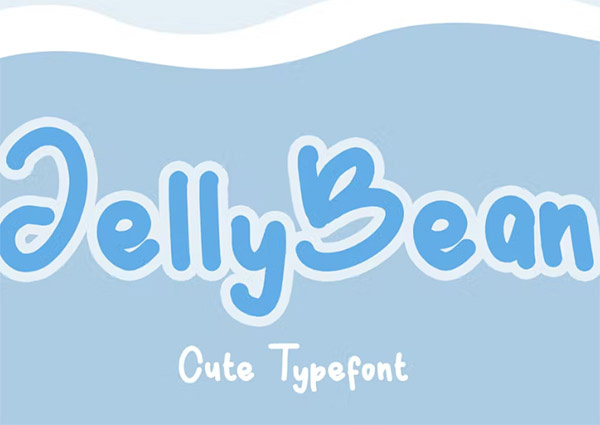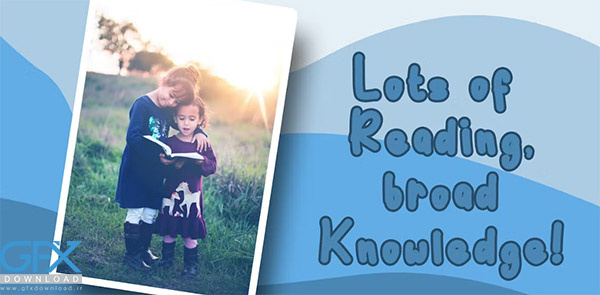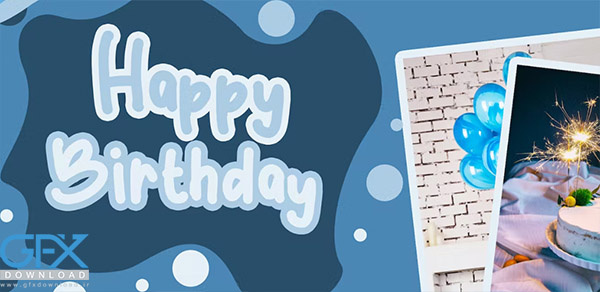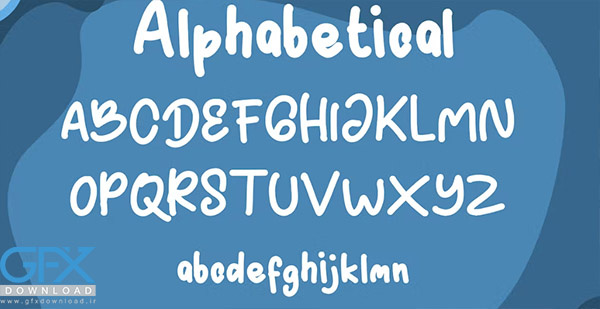
دانلود فونت بامزه JellyBean
فونت انگلیسی بامزه JellyBean
دانلود فونت انگلیسی بامزه و بازیگوش JellyBean
JellyBean یک فونت انگلیسی مناسب برای تمام طرح های سرگرم کننده شما است. فایل فونت اصلی مجهز به کاراکترهای معمولی و پشتیبانی چند زبانه است. دانلود فونت بامزه JellyBean برای استفاده در ساخت طرح تی شرت، نقل قول، برچسب، بسته بندی، نوع لوگو یا نوشتن بلند مناسب است. ویژگی های این پروژه : JellyBean OTF - TTF . JellyBean WOFF - WOFF2 . PUA کاملاً کد شده برای دسترسی کامل به همه کاراکتره.